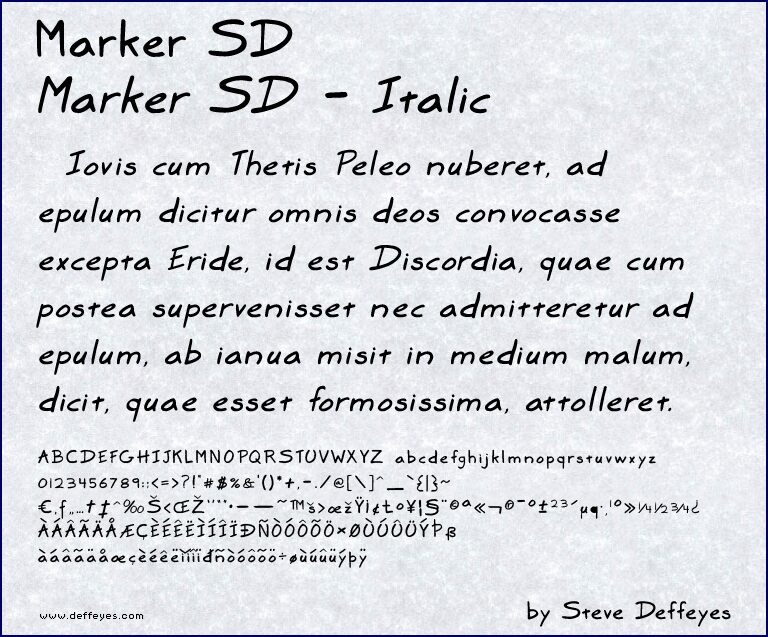
Marker SD von SD '98 ist eine kostenlose Handschrift-Schrift, die den lockeren Rhythmus schneller Marker-Schriftzüge einfängt – mit abgerundeten Strichen und einem beschwingten Auf und Ab. Die Linienführung bleibt stumpf und unkompliziert, sodass das Design wirkt, als sei es in einem Rutsch entstanden, statt mühsam poliert zu sein.
Dieser lässige Rhythmus passt perfekt zu notizartigen Überschriften, Café-Speisekarten, Unterrichtsmaterialien, Scrapbook-Titeln und informellen Verpackungen, bei denen eine ordentliche Schreibschrift zu steif wirken würde. Kurze Phrasen profitieren besonders von der breiten, handgezeichneten Dynamik, die Labels und Schildern eine direkte, alltägliche Stimme verleiht.
Meine eigene Handschrift, in einer sehr idealisierten Form!
Neu aktualisiert im August 2009, mit komplettem Zeichensatz und einer kursiven Variante.